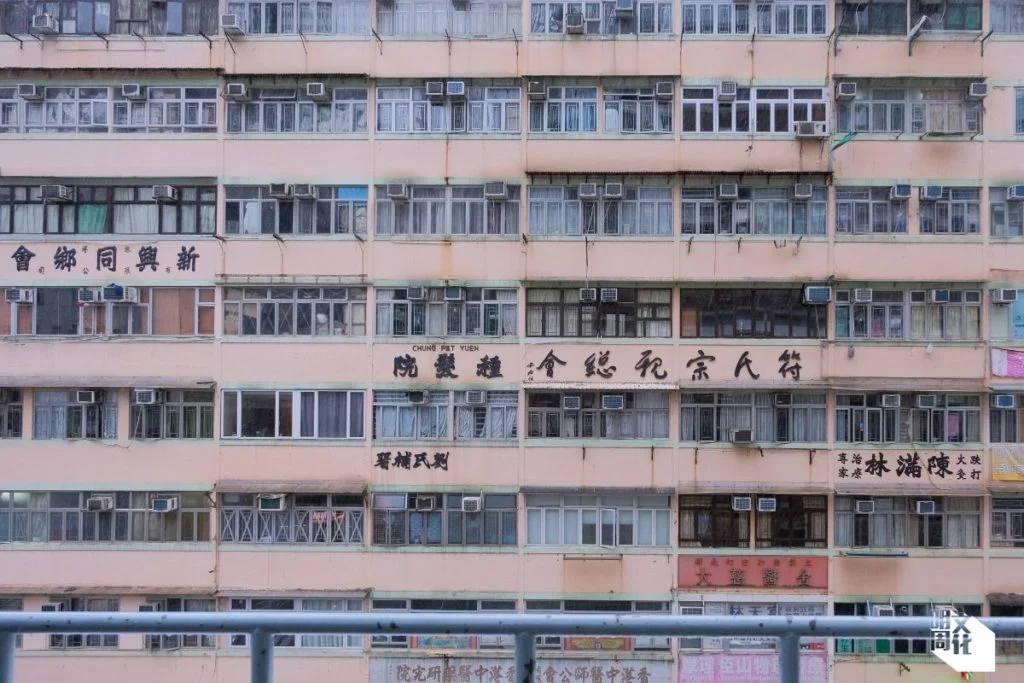
近年「港風」吹得起勁,不時看見遊客以霓虹招牌作背景興奮打卡,世界各地的港式茶餐廳也愈開愈多。神乎其技地,只要利用類似字體,就能大抵模擬出「港風」質感。字體,彷彿有種魔力。
香港街上風格各異卻自成派系的醒目招牌,一路都是我們別注的風景。其中一種最常見的香港招牌字體,叫「北魏」。字體設計師陳濬人(Adonian)自二〇一一年起研究北魏字體風格十餘年,兩年前以香港所見的北魏字體作為藍本創作電腦字體「北魏真書體」,在台灣集資平台獲得逾一百九十萬港元的眾籌金額支持。今年,「北魏真書體」終於釋出了它的第一個試用版本。
當霓虹熄了,我們能留下甚麼?
灣仔美華大廈外牆保留了多款手寫招牌字體。圖中所見「種髮院」幾字所用的,正是北魏體。
香港北魏真書的前世今生
「北魏真書」這個名字你未必聽過,但對它的字型風格,你肯定不會感到陌生,它存在於我們較熟悉的隸書和楷書之間。Adonian指,對於「真書」的定義,並沒有一個公認的共識。他自己則主張稱隸書演變成楷書中間的過渡時期之為「真書」,因為「北魏真書」兼有二者的成份和特色。「北魏」最初的原型來自魏碑,但魏碑的字體亦有多種風格。香港招牌常用的北魏,則靠近清代趙之謙版本的演繹。其時興仿摹魏碑字體,多追求模仿碑刻時的銳利感覺。趙則是少數認為字體演繹要有變化的書法家:「趙之謙是一個好artistic的人。他有很多嘗試,比如用很幾何的形狀去把字印出來。說的是百多年前,他已能實踐這種很graphical的做法。趙之謙給了(北魏)一個很破格的演繹。」
見於魏碑經典「龍門十二品」。
「北魏真書體」字體設計師陳濬人(Adonian)
清末民初,香港招牌書法家區建公等人從廣州等地南下來港,亦愛趙之書法,並在書寫香港招牌時保留和延續了他的風格。但香港招牌上的字體,與趙之謙的演繹又已有不同。Adonian稱北魏體在香港的變奏為「香港北魏真書」:「書法很有趣的是,就算是臨摹前人的風格,毛筆是軟的,你當中一定會有你自己的演繹。就好像趙之謙演繹魏碑會有不同,區建公他們演繹趙之謙又會有不同,大家都有自己的風格。」
招牌書法家區建公的著名作品「好到底麵家」。(網上圖片)
Adonian的電腦字體「北魏真書體」也是一種演繹。他「運筆」的重點並不在還原,而在於從演繹中注入屬於這個世代的動力,使字體真正鮮活起來:「我心裏面比較著重現代化那部分。」「Research不是太難,演繹的那部份最難。演繹完還要可以用到,是很難。我一直覺得這是延續文化最重要的部分。我們喜歡日本的文化,是因為它們很懂得去承傳他們自己的傳統。很多日本文化其實都是來自中國文化,而他們(日本人)就是很擅長做演繹的部份。我是想學日本人的這個精神。」
Adonian的電腦字體「北魏真書體」延續了香港北魏的特色,目的在重新演繹其神髓。
被問到北魏真書在香港應用為招牌字體的原因,Adonian認為是基於香港北魏的鮮明風格,「北魏真書體」集資的成功概亦歸功於此:「你可以幻想social media是一條很擠迫的街道,有很多文字、招牌、logo和字體想去捕捉大家的注意。(字體)應用在招牌,其實就像我們現在應用在social media一樣。在當時,作為招牌想要捕捉行人的注意,香港北魏的風格是很鮮明的。一些比較幼的楷書,也就是傳統楷書,你未必第一時間就會被它吸引。相比之下,香港北魏在一個城市環境裏面就很受注目。」
圖中「明苑」二字為香港北魏,與由一般電腦字體製作的現代招牌相比,更見其鮮明風格。
說到有強行懷舊之嫌的「港風」潮流,Adonian認為刻意「做舊」有時是一種不合時宜:「我不喜歡懷舊的東西,尤其看到現在的那些冰室,我是很討厭懷舊。」他所討厭的懷舊,是抱殘守缺,過份崇古而未能從舊設計煥發出現代美學意義的做法:「懷舊是要去懷緬,繼而懂得去欣賞。很多舊東西都是垃圾,我們要懂得去尋找當中的精髓和新的意義。找出來之後,就要看在當代社會可以怎樣去用。雖然這樣說有點自大,但我覺得『北魏真書體』是字體(懷舊)的一個示範。」,「很多建築、服裝、產品設計、顏色,都可以有這種做法:去研究過往的東西,再演繹成為新的東西。日本最強的就是這種做法,建築可以從舊的日本建築,演繹出新的建築,服裝就更不用説。我覺得香港很缺乏這一部分的努力。」
「北魏真書體」育成之路 慢慢來 比較快
Adonian大學時已對中文字體設計有興趣,最初並不知道街頭招牌上的字體風格叫「北魏」。只覺得好特別,就試著去描摹:「我那時連做法都不懂,直接拍一張招牌的照片,就在上面描。做一次就知,一定不能這樣去做。」不能直接上手,只好還原基本步。Adonian的「香港北魏真書」研究至今已歷時十餘年,從開始研究香港北魏,到出版香港北魏的研究及字體設計結集《香港北魏真書》花了六年。出書到「北魏真書體」beta版發佈的今日,又是另一個六年。
香港北魏研究及字體設計結集《香港北魏真書》,陳濬人、徐巧詩著。
相較於一般字體設計專案所耗費的時間,「北魏真書體」的育成之路走得漫長,卻是一步一腳印:「其實是有個進程的。由十幾年前開始,最初想做一個書法招牌地圖,所以才逐個區影。我影的方法真的是像scan那樣去影,整條街盡量影。最後我沒有做到地圖,但影了很多相。原因是那時開始做訪問,感覺多了人留意,也開始有其他人做(書法招牌地圖),那我覺得有人做就不再需要我去做。我一直都想做後面現代化那個部分。」在走訪街頭影招牌的同時,Adonian也去了學書法:「我不是為了做書法家,我是想打好根基。因為造字,其實最好是要知道所有(和字相關)的脈絡,你才知道怎樣去演繹,我做事比較喜歡逐步逐步。我經常覺得逐步逐步是最快的方法,快過走捷徑。如果直接造字,做得不好,還是要丟棄再做。」
走過的路自然都算數。Adonian當年影過的招牌,在「北魏真書體」面世前慢慢逐漸消失,那些相片最後成為了他字體設計時的獨家archive,亦組成了《香港北魏真書》一書:「最終目的都是造字,但是我知道件事有很多個階段。一就是我自己需要多點參考的material,二就是我要讓更多人知道這樣東西(香港北魏),出書就是要讓更多人知道。如果就這樣推出字體,大家唔知頭唔知路,都不會識欣賞。」
「我經常覺得,愈難的東西就愈有價值去做。雖然好痛苦,會不斷懷疑自己為甚麼要做這件事,但我覺得也是一個好好的鍛煉。所有耐看的作品都用了好長的時間去做,那種吸引力是要用很久去琢磨。」
被問到還記得第一組造的字是那些?Adonian說是香港,然後才是能在一個字中最大程度地囊括和表現所有筆劃類型的永、東等字(也是中文書法及字體設計常作為範例的一些字)。至於Adonian自己中文名中的「濬」字,他笑言:「未做過自己個名,因為好難做。」原來他也有知難而退的時候。
一撇一捺 當思來處不易
被問到字體以甚麼審美標準來製作,Adonian指造「北魏真書體」的美學考量離不開作為電腦字體的特性:「我做這套字一定是為了切合現代人的閱讀習慣,九成都是透過電子屏幕(讀到這種字體)。字印出來無論如何都會化開少少,而電子屏幕是sharp過印出來很多,所以(電腦字體)要做到乾淨俐落。」
Adonian會將字庫列印出來,便於審視整體字型效果,並在紙上標記,不斷地微調和「裝字」。
雕琢一個電腦字體,所花之力不亞於刻碑,也不是想像中手起刀落那麼快脆。尤其中文字體,不比英文只有基本二十六個字母,每個字、每個筆劃之間的平衡,都需要字體設計師再逐一親手協調。一個字的製作步驟,就「北魏真書體」而言,可以早到從用毛筆描摹開始:「最早的時候會先用毛筆寫一次那個字,讓自己了解筆劃的去向,然後再用鉛筆去sketch,畫一些outline。落實到電腦的時候,我不是(用字體的書法原型)墊在底,而是放圖片在側,大概有個感覺,在電腦再畫一次。」
Adonian描摹字體外型的草圖,旁邊不時附有他對北魏書法的一些觀察。
後來字庫變大,製作出一定數量的筆劃部件後,便可以不用重頭開始去做每一個字。但也不是像「筆畫輸入法」那樣,照樣組裝筆劃部件便完事,還要就每個字本身的構造,重新「裝字」。落實到實際應用,或是多於一個字的批量使用當中,就又需要再作相應的微調。所以是「.final」,「.final」,再「.final」,才終於有了今天的「Beta 1.0」。
本來想為這一部分定小題「十年磨一字」。轉念一想,相比起琢磨成千上萬個筆鋒,十年磨一劍,或許還更易。
「北魏真書體」的筆劃部件庫。
北魏真書究極體?藝術沒有最終章
Beta版發佈啟用後的下一步動作是甚麼,理所當然是update版本以待正式推出。那麼正式推出之後呢?Adonian竟說最理想是像iOS一樣不斷有更新,只是未必有這個心力:「大部份人對於一個作品,都會覺得有完成的一日。做一套字體,就始終會出現一套已經完成的字體,但我並沒有這個想法。一件作品是可以不斷地refine,沒有停止的一日,你看到的永遠只是它整個進程的其中一部分。這個概念是我從盆景中學會的。盆景就是你看到的只不過是它作為植物的其中一個時刻、一個狀態。只要它未死,它一直都在變化。」
「如果你keep住去參與,去用這個字體,每一份參與,每一個人去看,都是一個新的創作。」從Adonian將每一個「北魏真書體」由書法轉化成活字的那一刻,這些字就會一直在不同使用場景中,更多人的生活裏,「活」下去而沒有最終章。「北魏真書體」作為字體的生命力如有旺盛,也是滋養自我們重要的文化圖景——香港招牌。
如此這般,透過字體設計的藝術,我們或能為我地留下些甚麼。